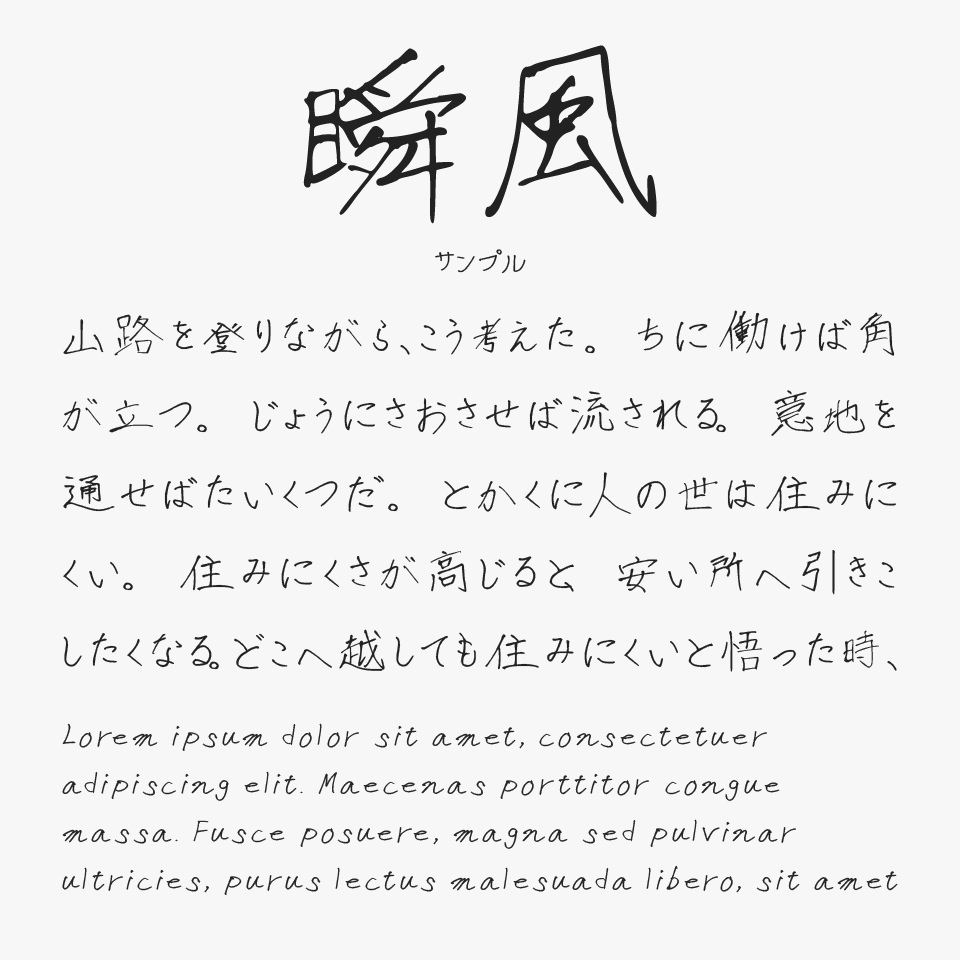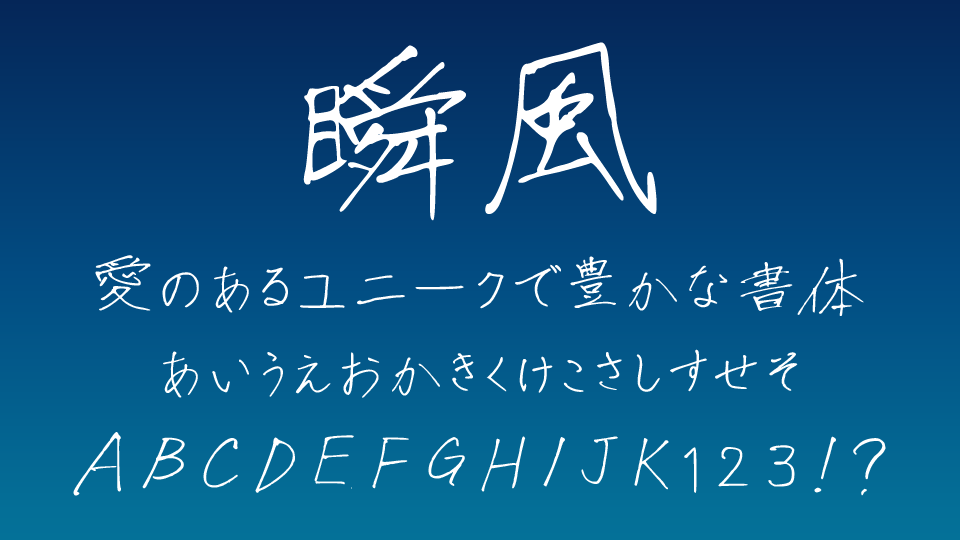
瞬風フォントは、風が吹き抜けるような毛筆の勢いのある躍動感あふれる手書きフォントです。
払いや跳ねにはインクの墨溜まりやかすれが残っているのがとてもリアルな質感があるフォントです。サッと筆先が流れるような筆致は「速さ」を感じられて、かっこよくもある手書きフォントです。
収録文字は、ひらがな・カタカナ・アルファベット・数字・記号が収録されています。
【有料版】では、JIS第二水準までの漢字を収録(6700文字以上)されています。